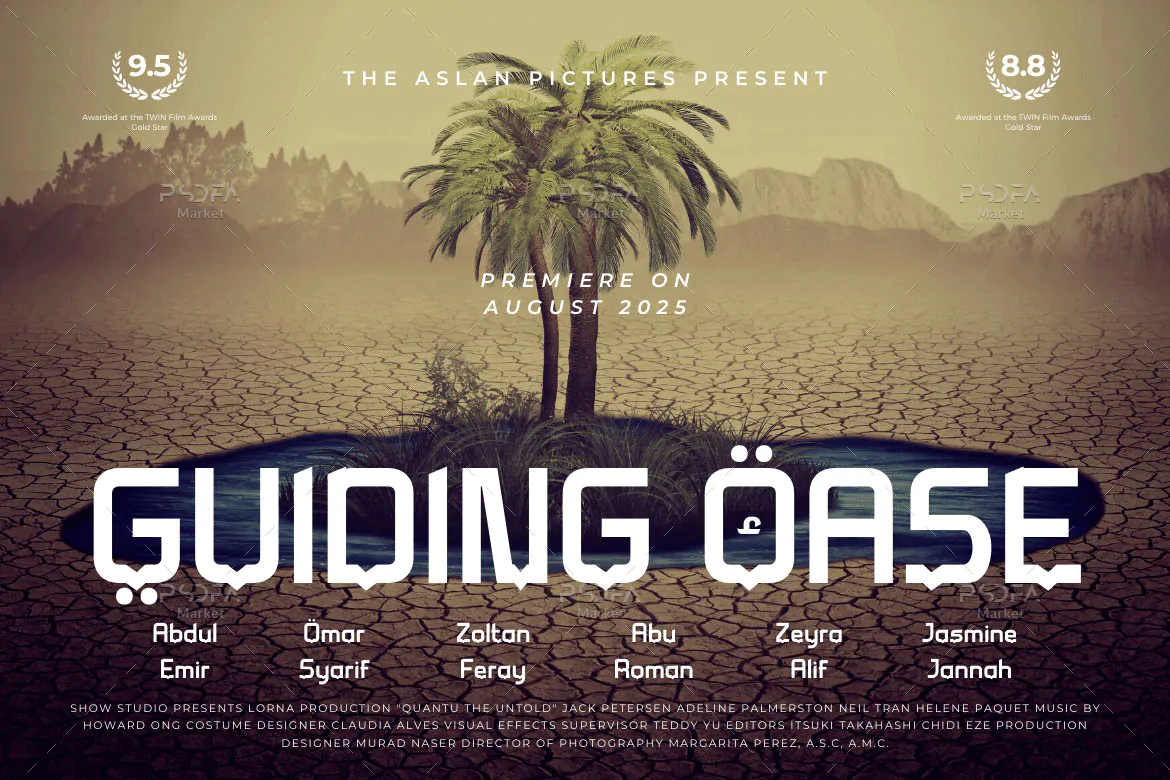
فونت انگلیسی کویتی به سبک و استایل عربی
فونت انگلیسی کویتی
فونت انگلیسی کویتی یک قلم نمایشی فوق العاده زیبا است که به سبک و استایل فونتهای عربی طراحی شده است و مناسب جهت استفاده در طرحهای گرافیکی مختلف میباشد. فونت Koweti با وزن معمولی طراحی شده است که از آن میتوانید در طراحی انواع پوستر، کارت ویزیت، بنر، تراکت، بروشور، آرایشی و بهداشتی،بسته بندی محصولات و … استفاده کنید.